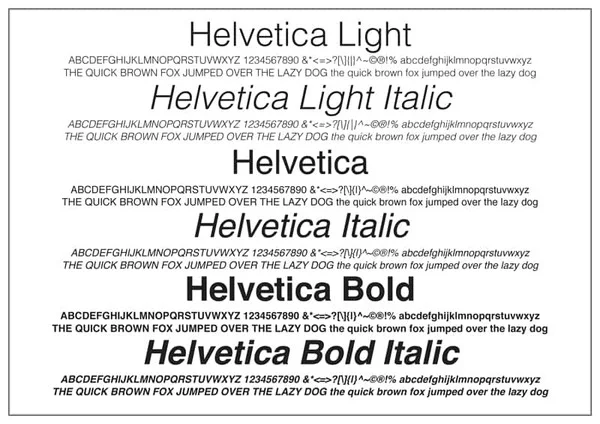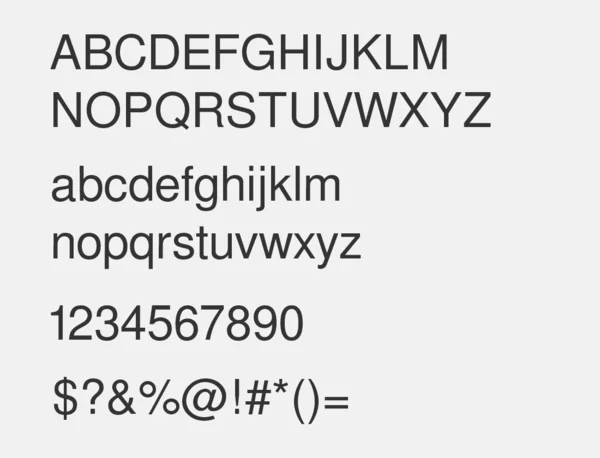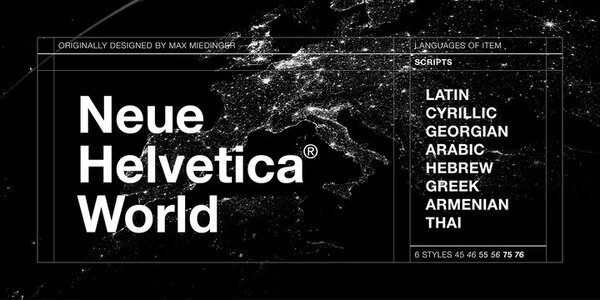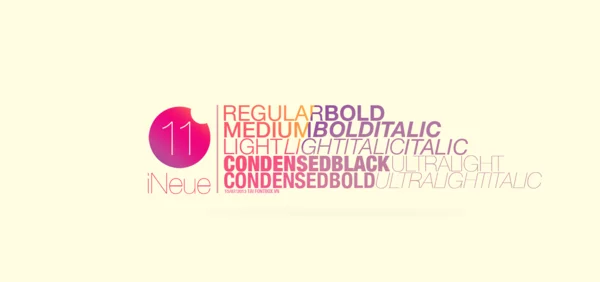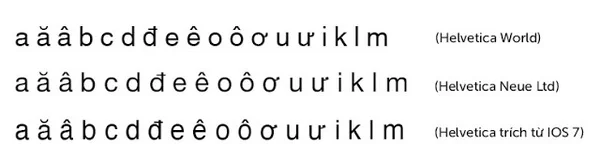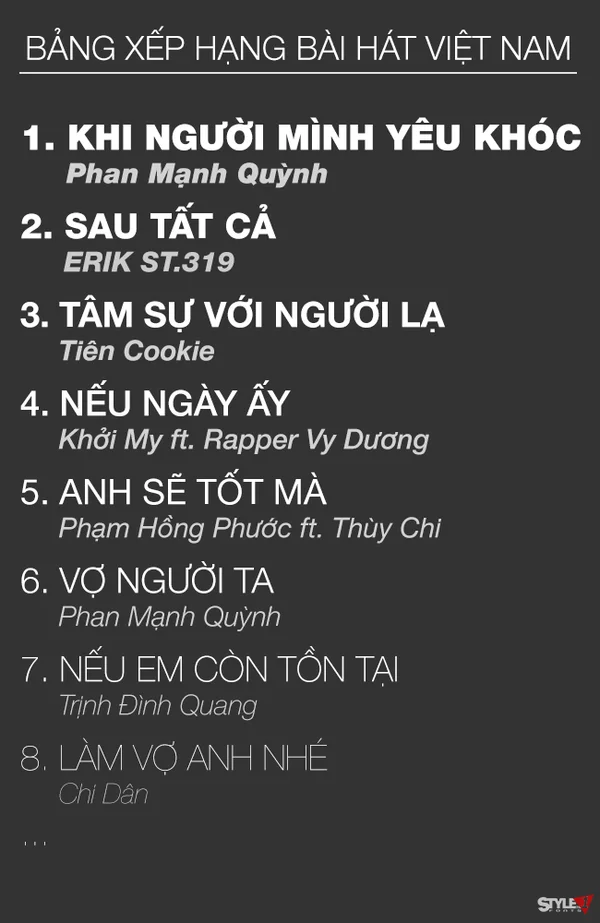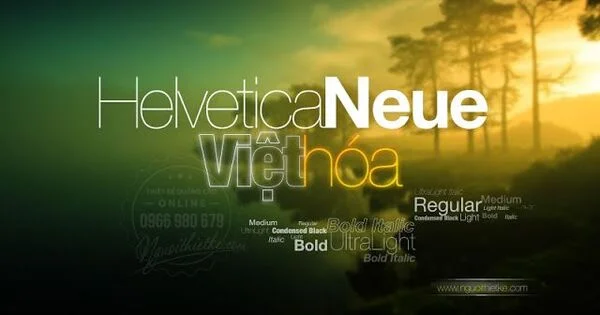
Helvetica font là một trong những font chữ lâu đời, được sử dụng nhiều nhất và nổi tiếng nhất trên thế giới cũng như Việt Nam. Đây là bộ font cơ bản và dễ sử dụng cho nhiều mục đích khác nhau. Vì vậy, Helvetica font trở thành bộ font không thể thiếu đối với dân thiết kế nói riêng hay dân văn phòng nói chung. Trong bài viết này, Printgo sẽ giới thiệu sơ lược về Helvetica font cũng như gửi đến các bạn link download font Helvetica miễn phí đẹp và mới nhất ở cuối bài.
Font Helvetica là font chữ dạng Sans-serif được sử dụng nhiều nhất hiện nay trên thế giới và Việt Nam. Vì những ưu điểm của nó mà Helvetica font đã được Việt hoá và trở nên phổ biến và có nhiều người sử dụng hơn tại Việt Nam.
Helvetica font có nhiều điểm khác biệt so với các font chữ khác như chữ G có nét thẳng ở dưới chân hay chữ A sẽ có nét cong và tròn ở phần chân và bụng. Helvetica font được sử dụng với nhiều mục đích khác nhau tùy thuộc vào trường hợp thiết kế hay sử dụng. Cũng chính vì lý do này mà font Helvetica được sử dụng trong rất nhiều bối cảnh khác nhau. Bằng chính là Helvetica font là một trong những font chữ Typeface có số lượng biến thể nhiều và đa dạng nhất trên thế giới.